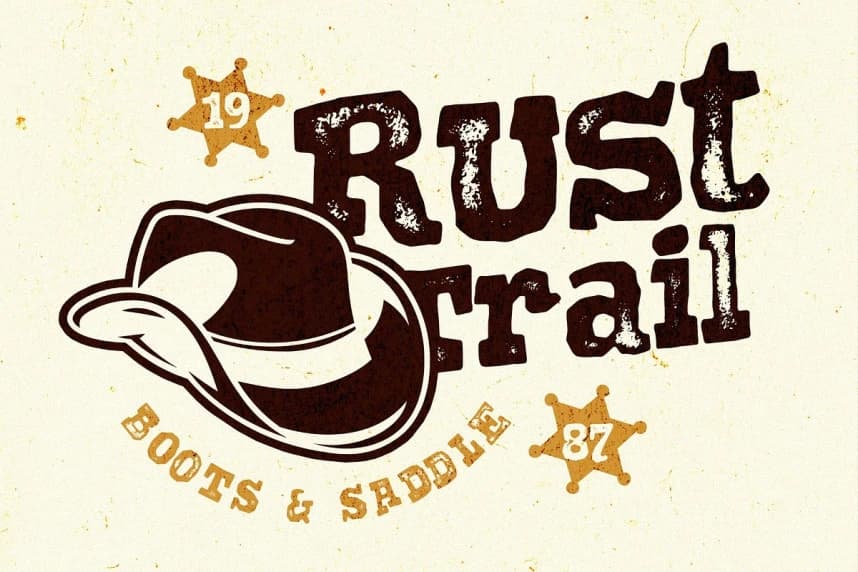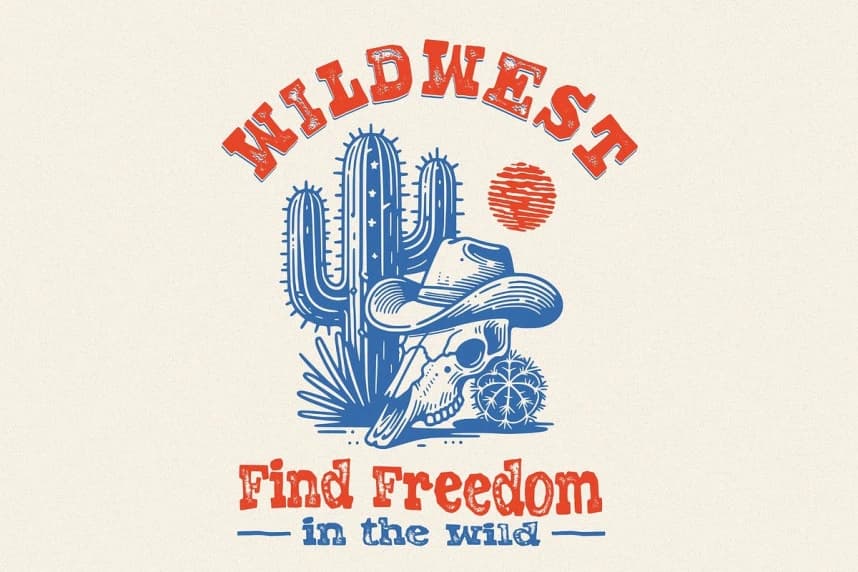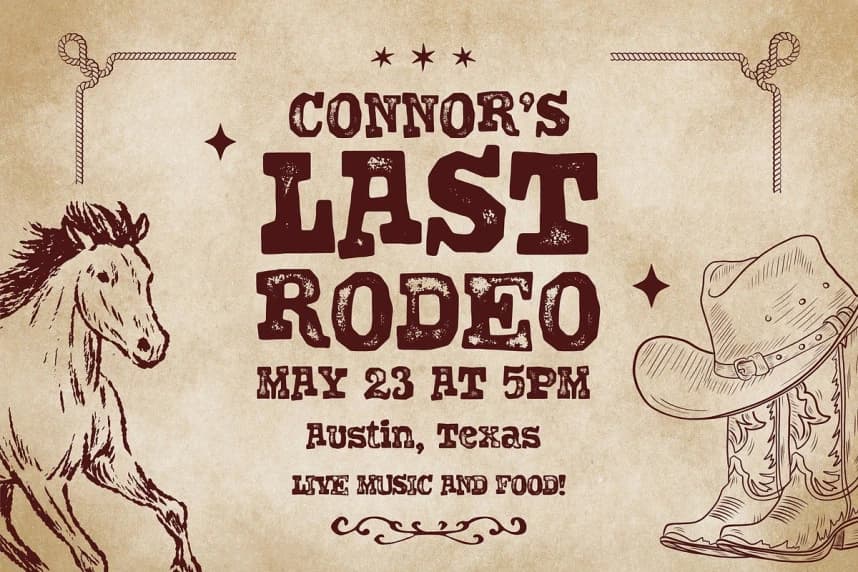
Dodgy Distort Font
Dodgy Distort Font, vahşi batı temalı karizmatik bir yazı tipidir ve sınırın tozunu, sertliğini ve özgüvenli tavrını parmaklarınızın ucuna getirir. 803 glife sahip ve 104 dili destekleyen bu yazı tipi, sadece konuşmakla kalmaz; hızlıca çizer.
Dodgy Distort Font, vahşi Batı'ya özgü son derece karizmatik bir yazı tipidir ve sınırın tozunu, sertliğini ve kendine güvenen tavrını parmaklarınızın ucuna getirir. 803 glife sahip olması ve 104 dili desteklemesiyle, bu yazı tipi sadece konuşmaz, hızlıca çizer.